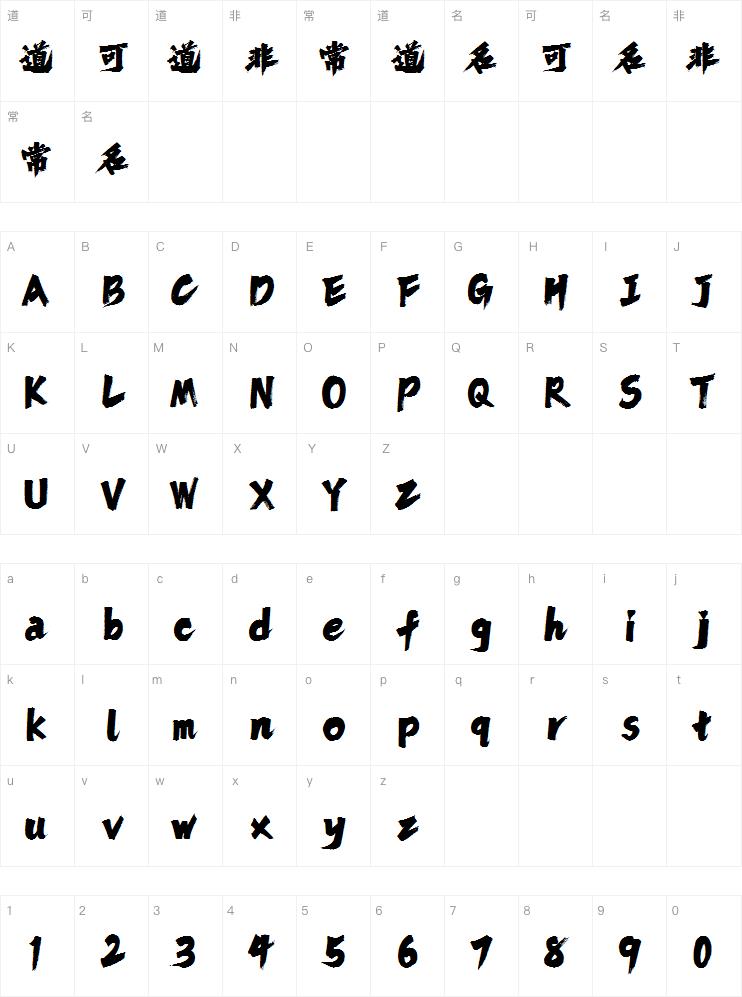
潮字社黯然销魂简繁 挥洒是一款张扬率意,满溢武侠气息的毛笔字体。书写下笔极为用力,粗犷极意,黑色笔画如狂风骤雨般袭来,飞白贯穿于笔画之中。结体狂放张扬,整体笔势向右上夸张的扬起,肆意张扬、形态多变。带给读者如身处刀光剑影的武侠世界中,于凶险紧迫的氛围中,有感受到冲天的侠气与张狂不羁意境。适用于影视宣传、游戏宣传以及文创、包装设计等多种应用场景 。